塩の花 焦がしミルクと塩チョコ / 塩の花 みたらしミルク
「塩の花 焦がしミルクと塩チョコ」「塩の花 みたらしミルク」はUHA味覚糖による塩スイーツ。
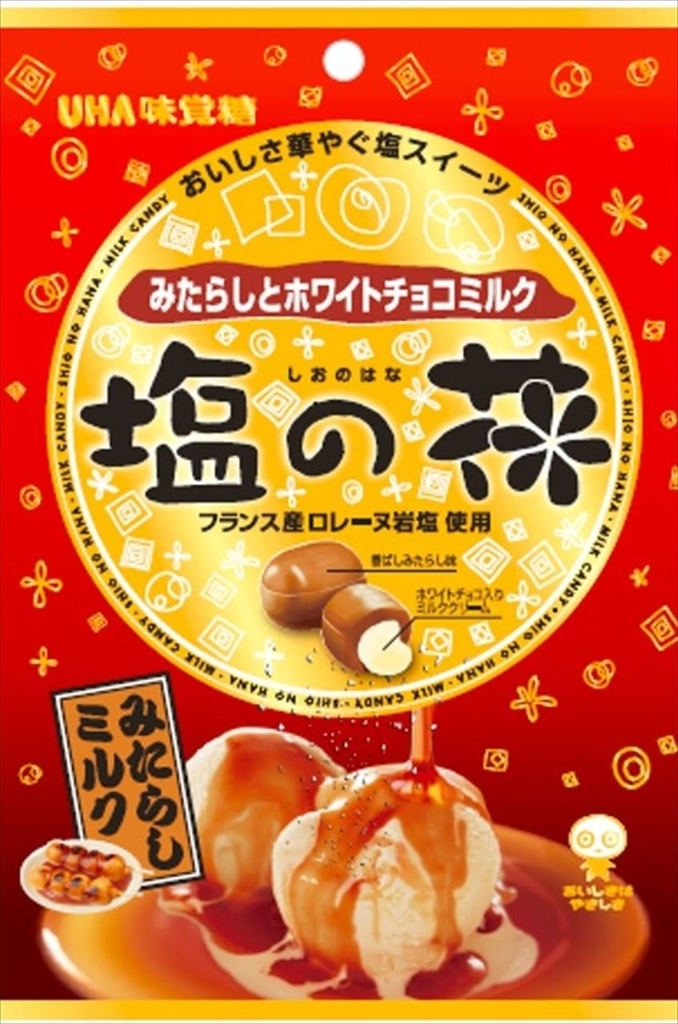
「塩の花 焦がしミルクと塩チョコ」は、味わい深い焦がしミルクに塩チョコレートが入ったリッチなキャンディ。
フランス産ロレーヌ岩塩を使用し、チョコが溶けても塩の余韻が贅沢に残る。
塩の花のみたらし味。香ばしいみたらし味のキャンディにホワイトチョコ入りクリームを入っており、あまじょっぱい味わいが楽しめる。
塩の花シリーズのタイトルにダイナフォントクラフト墨が採用 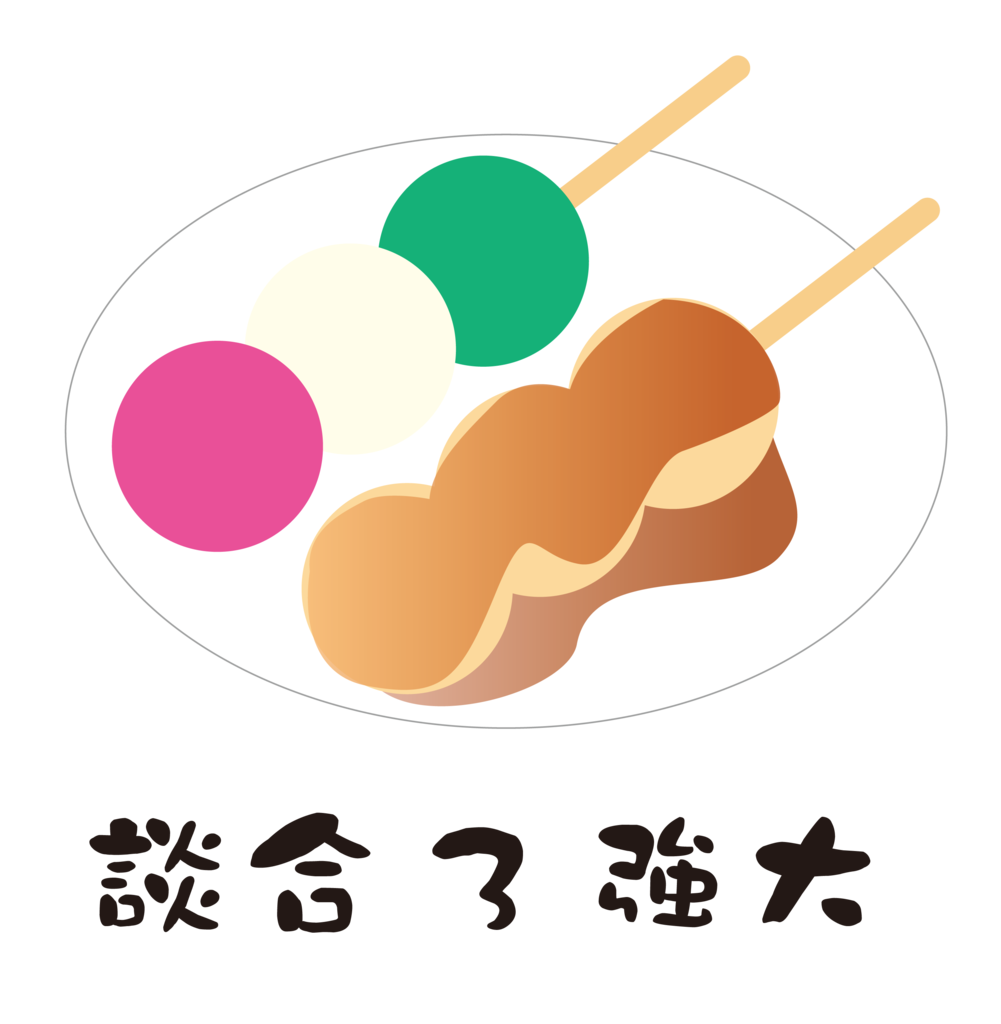
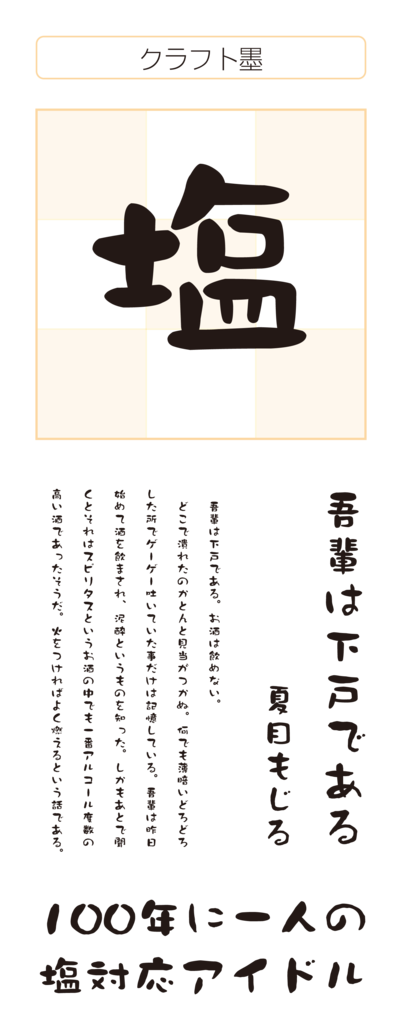
UHA味覚糖株式会社が製造・販売する「塩の花 焦がしミルクと塩チョコ」「塩の花 みたらしミルク」にダイナフォント クラフト墨が採用されている。
クラフト墨
書道本来の構成や書き方に変化を加え、文字の面白さや破調を表現した書体。線の長さや「へん」「つくり」などの部首に字形を崩す程の変化を加えている。また空間の取り方も独特で、丸く豊かな運びによってかわいらしく、リラックスした雰囲気が引き出され、墨字の躍動感も表現されている。